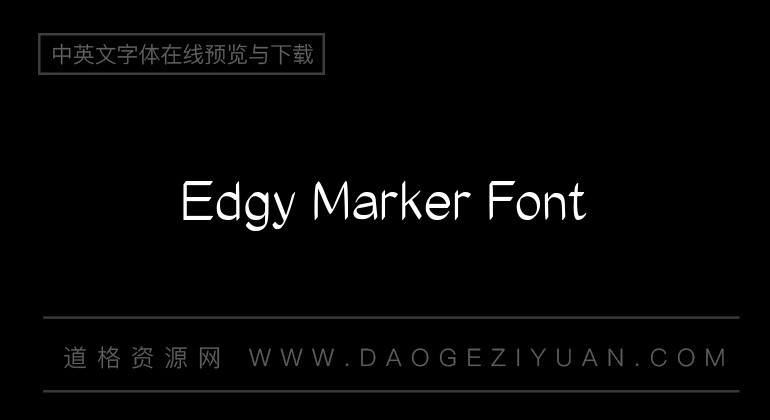
Edgy Marker Font 是一种手写风格的字体,它的特点是具有边缘感和不规则线条。这种字体常用于设计中,尤其是对于那些希望传达非正式、年轻、时尚或艺术气息的品牌或项目而言。 Edgy Marker Font 的字形看起来像是用马克笔或毛笔书写的,而且其线条不太规则,非常自然,让人感觉到有一种独特的个性和表现力。这种字体常用于海报、标签、包装设计等场合,以突出其独特性和个性化的特点。 总的来说,Edgy Marker Font 是一种非常有特色的字体,适用于各种不同的设计场合,尤其是那些需要突出非正式、时尚、年轻或艺术气息的品牌或项目。内容介绍
Edgy Marker Font是一款非常不错的手写艺术字体,具有很好的视觉感,适合于文化类的宣传设计、商业类品牌的广告和产品包装设计以及个性化文字排版等较多场景。